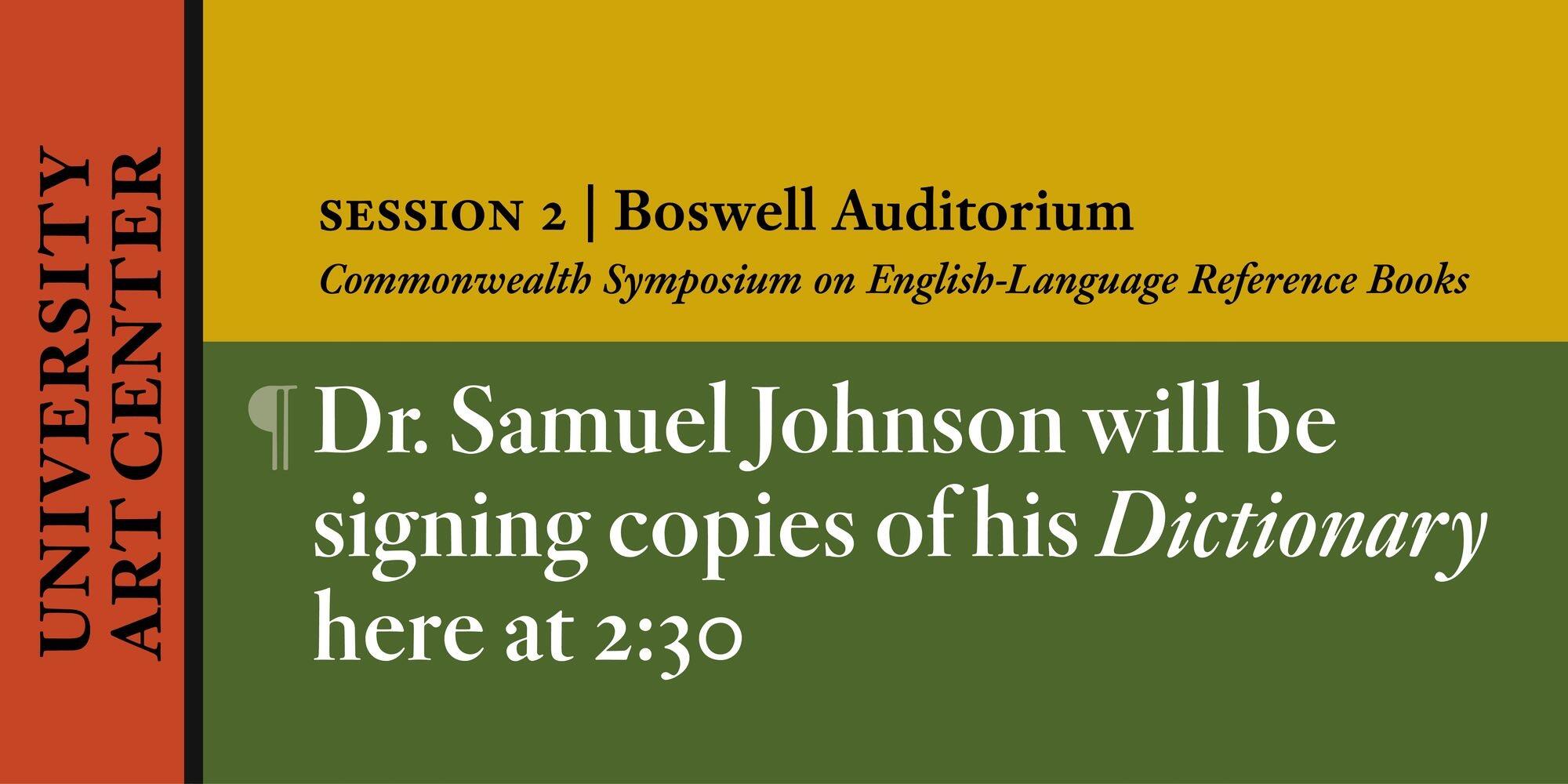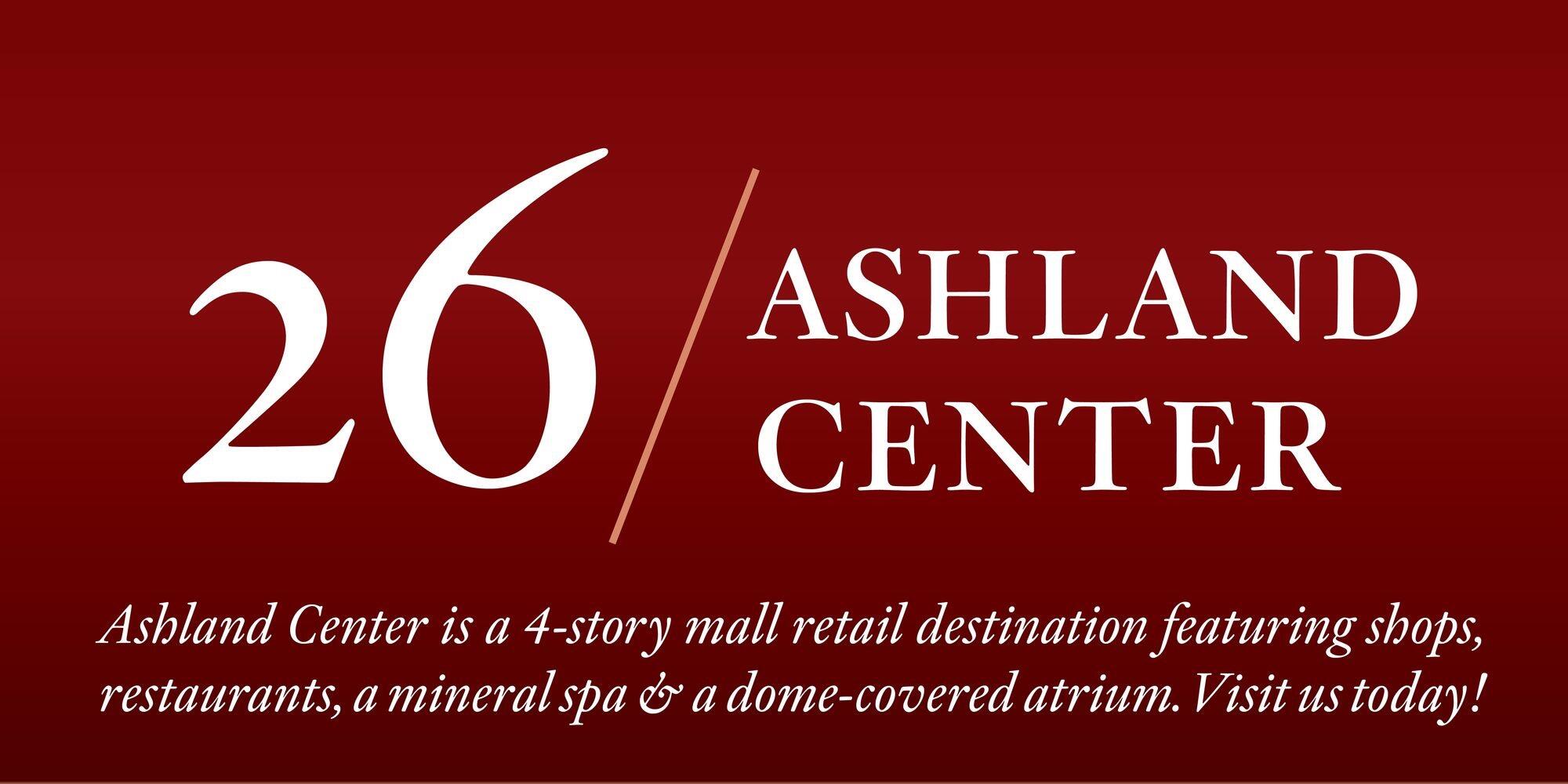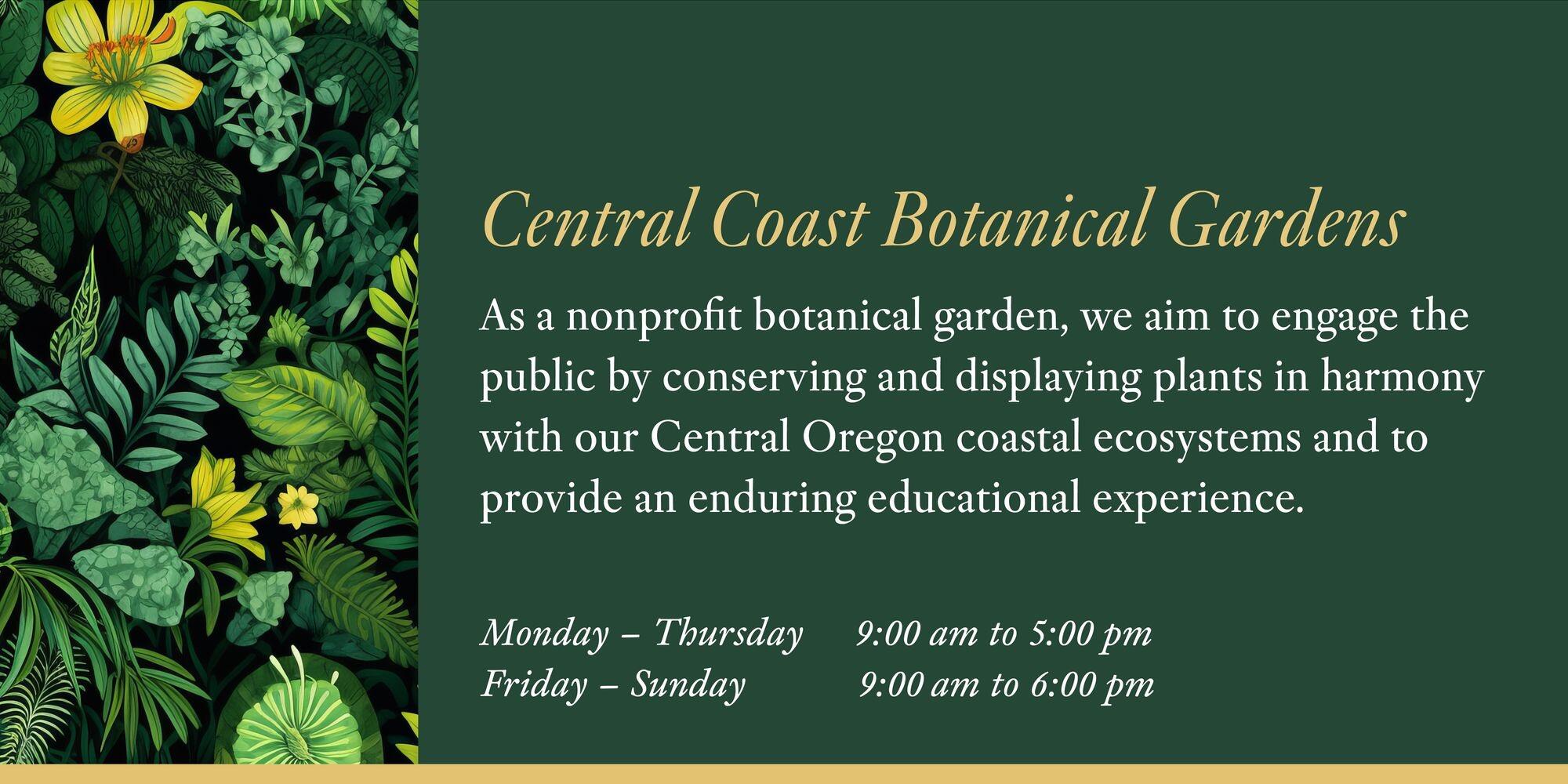
Die Adobe Kis ist eine Neubearbeitung der Schriften von Nicolas Kis aus dem 17. Jahrhundert durch Robert Slimbach. Das Design verfügt über drei Strichstärken mit Kursiven, die sich über vier optische Größen erstrecken. In der Summe kommt die Familie so auf 24 Schnitte. Alternativ können auch die beiden variablen Fonts verwendet werden.
Zum Zeichenvorrat gehört eine erweiterte lateinische Belegung mit mehreren Ziffernsets und Kapitälchen. Ein großes Eszett ist jedoch nicht enthalten.